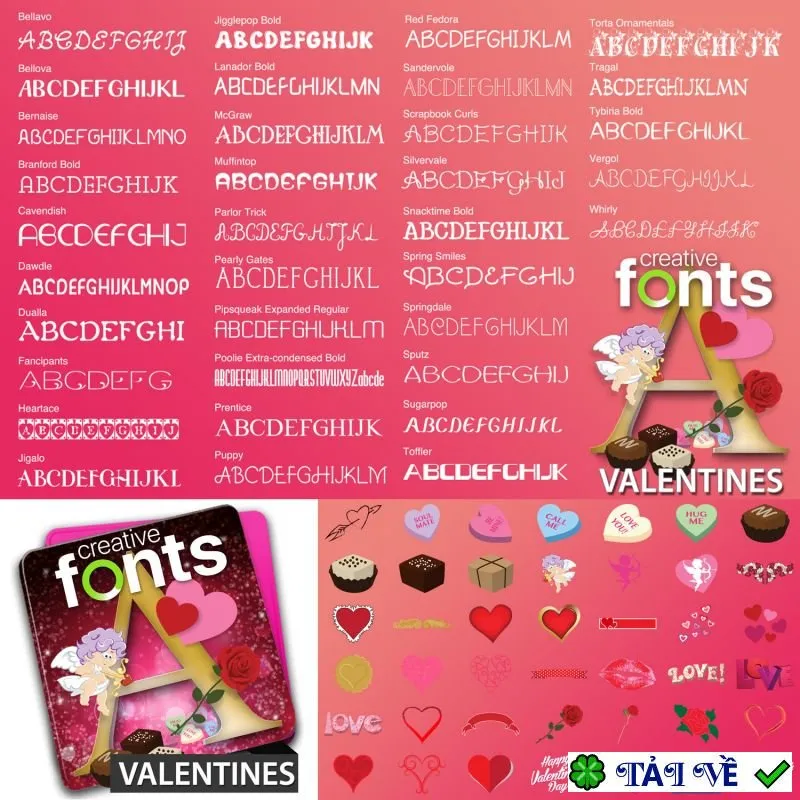
Bạn đang tìm kiếm những phông chữ độc đáo để làm bừng sáng các dự án sáng tạo của mình? Bộ sưu tập Summitsoft Creative Fonts Collection 2025 mang đến hàng ngàn kiểu chữ nghệ thuật, được thiết kế chuyên nghiệp và đa dạng phong cách, từ chữ viết tay mềm mại đến sci-fi ấn tượng ?, fantasy kỳ ảo ? và cả phong cách truyện tranh vui nhộn ?. Tất cả đều đạt chuẩn OpenType sắc nét, dễ dàng cài đặt và sử dụng trên mọi phần mềm, đặc biệt là giấy phép sử dụng cho cả mục đích cá nhân và thương mại. Hãy nâng tầm thiết kế của bạn với bộ sưu tập phông chữ độc quyền này!
Tổng quan về Bộ sưu tập phông chữ Summitsoft Creative Fonts Collection:
Summitsoft Creative Fonts Collection là tuyển tập các phông chữ tuyệt mỹ, được thiết kế bởi đội ngũ chuyên nghiệp tại SummitType Foundry. Bộ sưu tập này mang đến cho bạn những lựa chọn phông chữ hoàn hảo cho mọi dự án, cùng với các hình ảnh minh họa (clip art) theo chủ đề, giúp tăng thêm sự phong phú cho tác phẩm của bạn.
Đội ngũ sáng tạo của SummitType Foundry, thuộc Summitsoft, là những người trực tiếp thiết kế và sản xuất từng phông chữ trong bộ sưu tập này. Mỗi kiểu chữ đều mang nét độc đáo riêng, không thể tìm thấy ở đâu khác, biến Creative Fonts Collection thành nguồn tài nguyên quý giá cho những dự án đòi hỏi sự khác biệt.
Các tính năng nổi bật của Summitsoft Creative Fonts Collection:
- Bộ sưu tập bao gồm đa dạng phong cách độc đáo như phông chữ cổ điển, chữ viết tay nghệ thuật, sáng tạo, thiết kế ấn tượng và chữ viết tay cá tính.
- Các phong cách đặc biệt khác bao gồm phông chữ khoa học viễn tưởng, vui nhộn, thể thao, ấn tượng, dành cho game và truyện tranh.
- Các phông chữ theo chủ đề mùa lễ hội với phong cách độc đáo và clip art đi kèm, ví dụ như Giáng sinh, Mùa xuân, Halloween, Lớp học, Lễ tình nhân và Đám cưới.
- Tất cả phông chữ trong bộ sưu tập đều tuân thủ chuẩn OpenType, tiêu chuẩn công nghiệp được Microsoft® và Adobe® tin dùng. Điều này đảm bảo phông chữ luôn sắc nét và rõ ràng ở mọi kích thước.
- Mỗi phông chữ đều bao gồm bộ ký tự đầy đủ, hỗ trợ tất cả các ký hiệu quốc tế, ngôn ngữ nước ngoài và các ký tự đặc biệt.